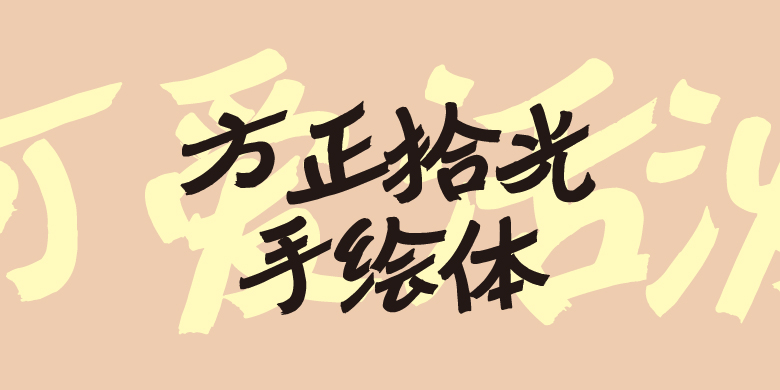
方正拾光手绘体
字体品牌: 方正字库 设计师:梁风波 字体分类:创意字体 字体属性:精品字 字符集:大陆简体(GB2312-80) 发布时间: 2026
这款字体是第12届方正奖专业入围作品。最初源于儿童画笔的涂鸦手绘字样。经扫描进电脑处理后,独特的未涂满的斑驳纹理跃然纸上,恰似孩子随性创作留下的痕迹,自然质朴的魅力油然而生。因其结构跳脱常规,如孩子般无拘无束的时光,笔画生动活泼,可爱气质尽显,充满了童真趣味。无论是儿童读物、亲子活动海报,还是各类创意设计,这款字体都极为适配,能为作品增添独特的活力与欢乐。